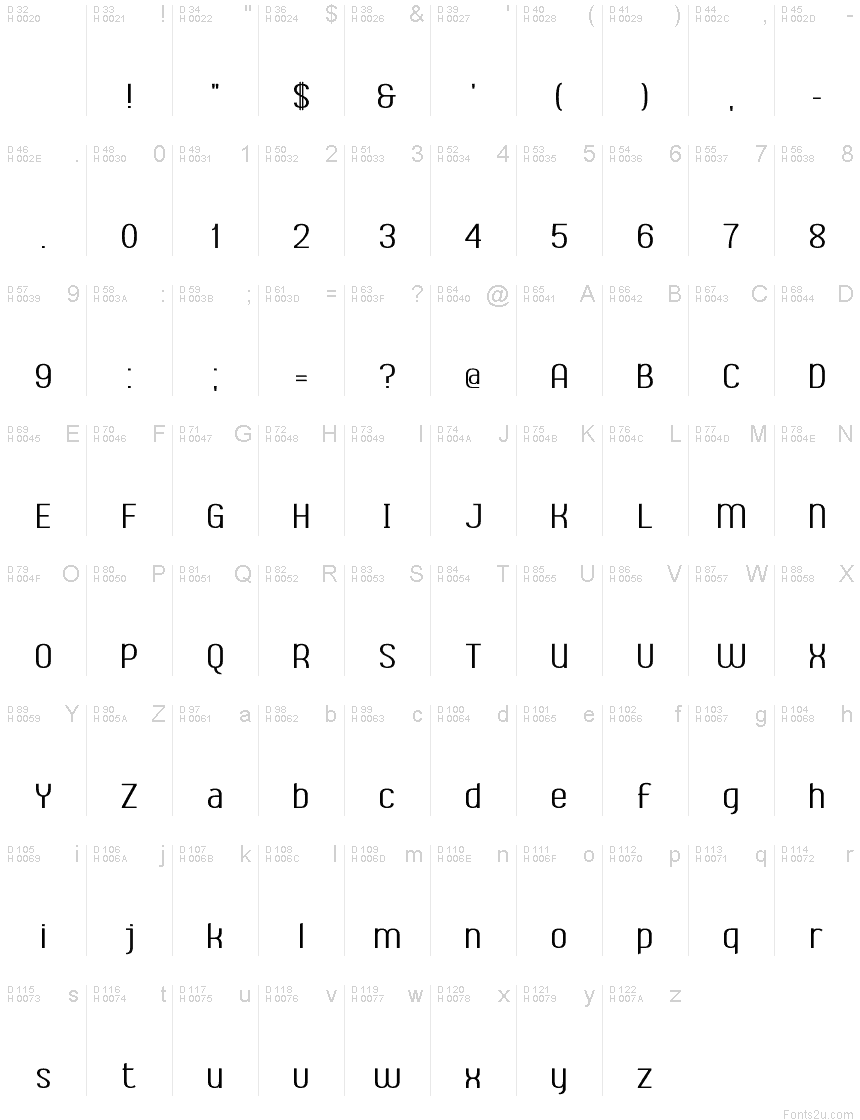
خط Ambrosia من تصميم Tjarda Koster هو خط sans serif يحوّل أشكال الحروف البسيطة إلى تصميم هادئ ومميز. تتسم نسبه بالطول والنحافة، وتلطفها الزوايا المستديرة بسخاء والفراغات المفتوحة داخل الحروف، مما يمنحه مظهراً نقياً وراقياً في آن واحد - أشبه بالحبر اللامع على ورق أملس. يوفر سمك الخط المتساوي والمساحات المنظمة مظهراً عصرياً وواضحاً، بينما تضفي المنحنيات الدقيقة لمسة دافئة وإنسانية.
مع خط Ambrosia، ستحصل على خط sans serif يتميز بالأناقة وسهولة الاستخدام في العلامات التجارية (Branding)، والتغليف، والعناوين التحريرية، والنصوص البارزة في المواقع الإلكترونية، والملصقات، وشعارات الكلمات (logo wordmarks). يتألق هذا الخط المجاني عند استخدامه بأحجام أكبر، مما يتيح لتلك الأشكال المستديرة أن تتنفس، كما يتناسب بشكل طبيعي مع خطوط الـ grotesk المحايدة أو الخطوط الهندسية sans الخفيفة للنصوص الأساسية.